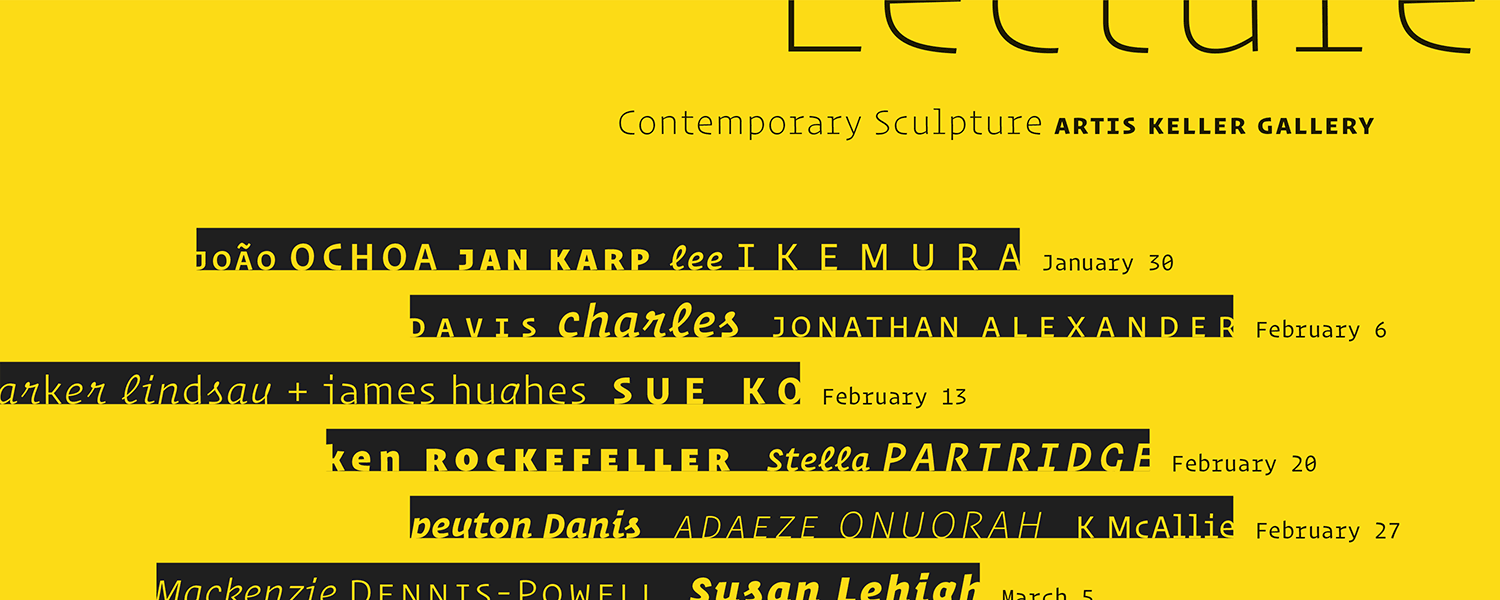
I caratteri a spaziatura fissa, nati per le macchine da scrivere, spesso usati per associare visivamente concetti legati al giornalismo, l’ambito legale o il mondo accademico, oggi sono soprattutto i caratteri dei codici di programmazione.
Per realizzare Operator Mono, dice Hoefler, non hanno guardato solo alle vecchie macchine da scrivere, ma hanno lavorato pensando a designer e sviluppatori e si sono ritrovati a parlare spesso Javascript e Css.
[quote]In developing Operator, we found ourselves talking about JavaScript and css, looking for vinyl label embossers on eBay, renting a cantankerous old machine from perhaps the last typewriter repair shop in New York, and unearthing a flea market find that amazingly dates to 1893.[/quote]
Operator Mono è disponibile in 9 pesi, con corsivi e maiuscoletto. Sotto è possibile vederlo all’opera su Atom (il text editor di GitHub).
Molto interessante anche il video che racconta la genesi del font.